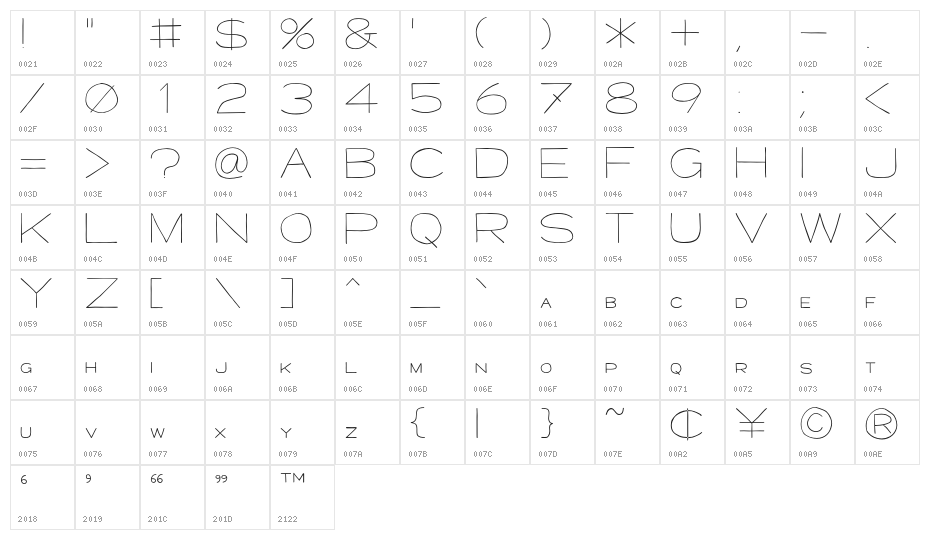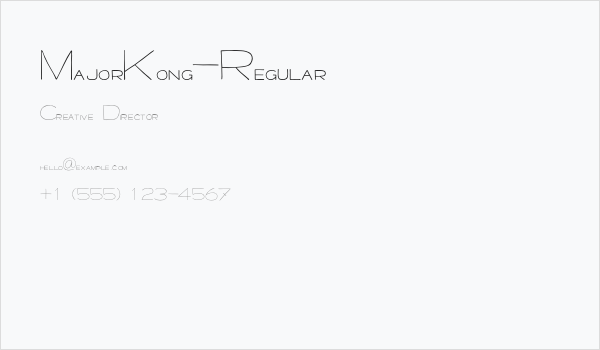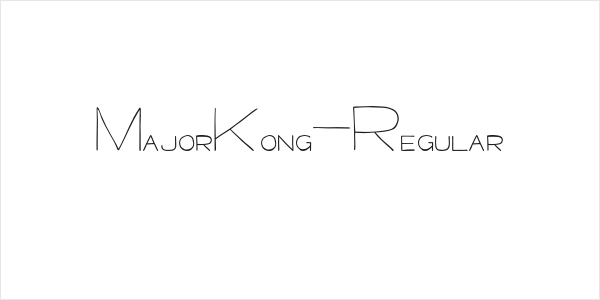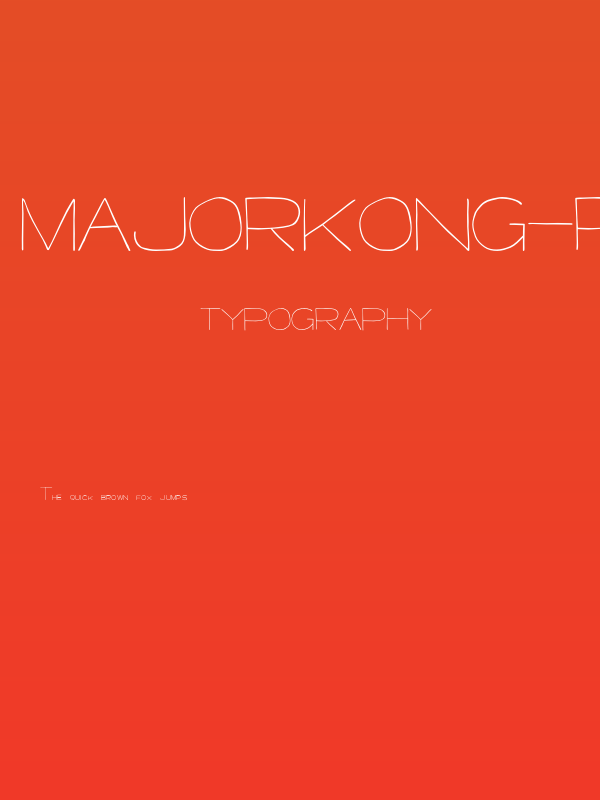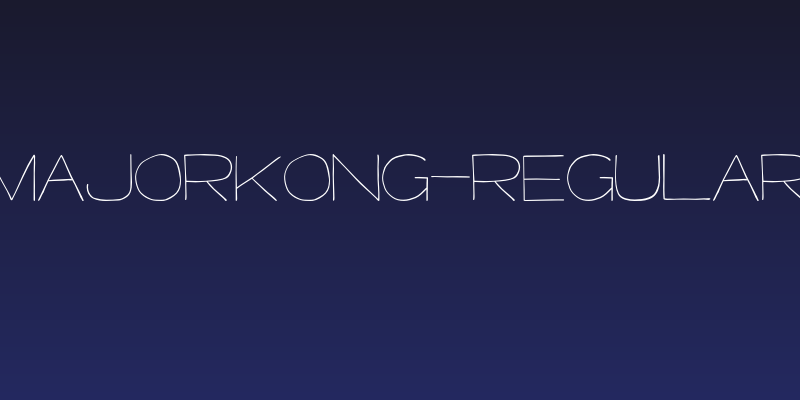
MajorKong-Regular Font
| Stile generale | Futuristic and technical |
| Caso d'uso | Headlines, Logos, Digital displays |
| Progetti proposti | Ideal for tech branding, digital interfaces, modern advertising, and futuristic designs. |